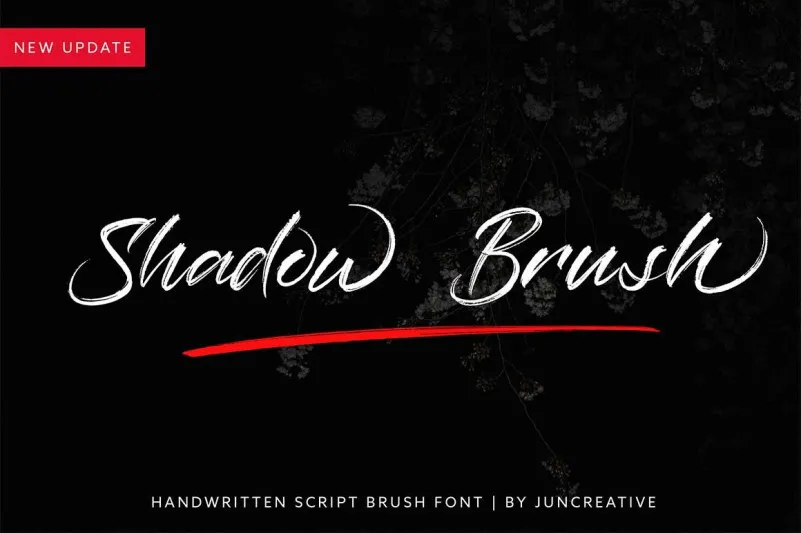
Shadow Brush Font – Fonte Grátis
Shadow Brush Font
Essa fonte ‘Shadow Brush Font’ é perfeita para projetos que buscam uma sensação natural e elegante. Ela pertence à categoria de fontes de script, criada pelo designer 99designs, destacando-se pela sua textura realista e detalhada, fornecendo um contraste entre a casualidade e o encanto na composição de letras. O design inclui uma linha sobrenatural que flui de forma orgânica ao longo das letras, além do tradicional acabamento com pincel. Através dessas características, essa fonte oferece um equilíbrio perfeito entre os aspectos informais e fascinantes em projetos gráficos, fazendo-a uma escolha ideal para designers buscando um toque natural na sua arte digital.